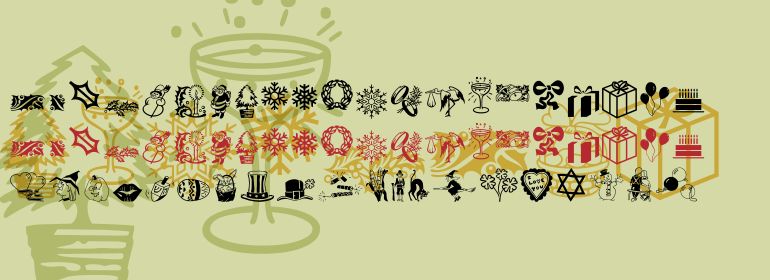
Holidays™
Holidays™,这款字体结构工整、笔画清晰,兼顾美观与易读性,适用于标题、正文、海报、包装、LOGO 等多种场景。字形优雅稳定,风格百搭耐看,适配日常排版与创意设计,让文字呈现更舒适、更具质感。Holidays™一笔一画,皆是细节,以均衡的比例、流畅的线条打造舒适视觉体验,字形端正大气,风格简约现代。无论是商业设计、品牌宣传还是日常排版,都能轻松驾驭,让文字更有格调与力量。Holidays™字体下载。